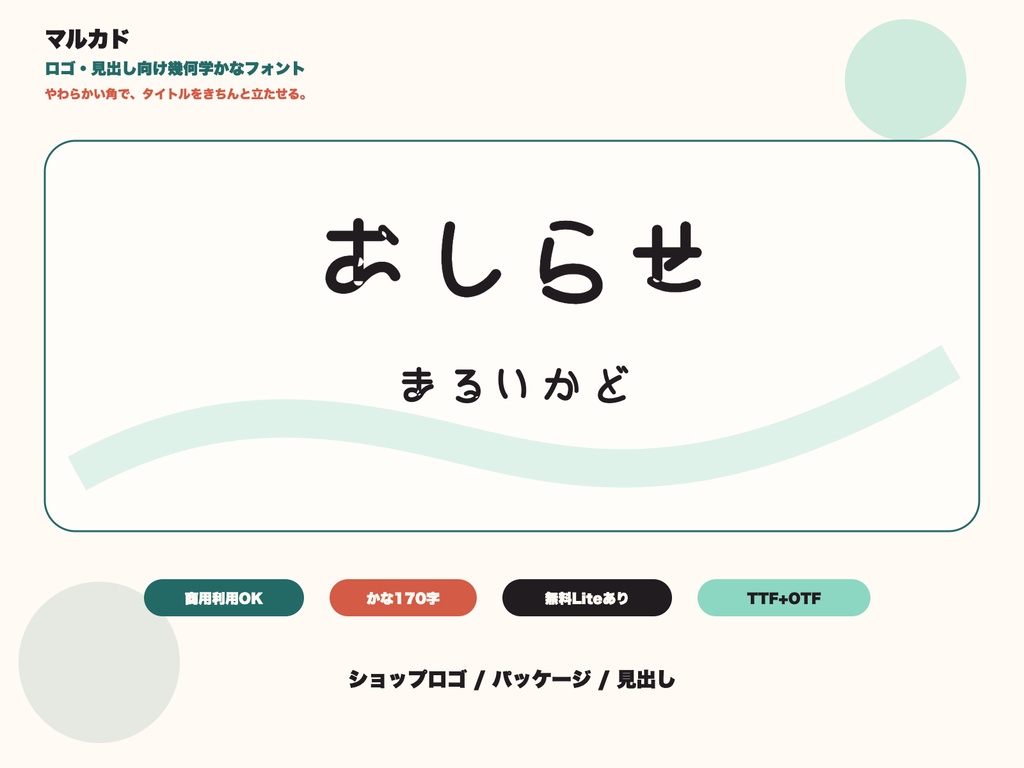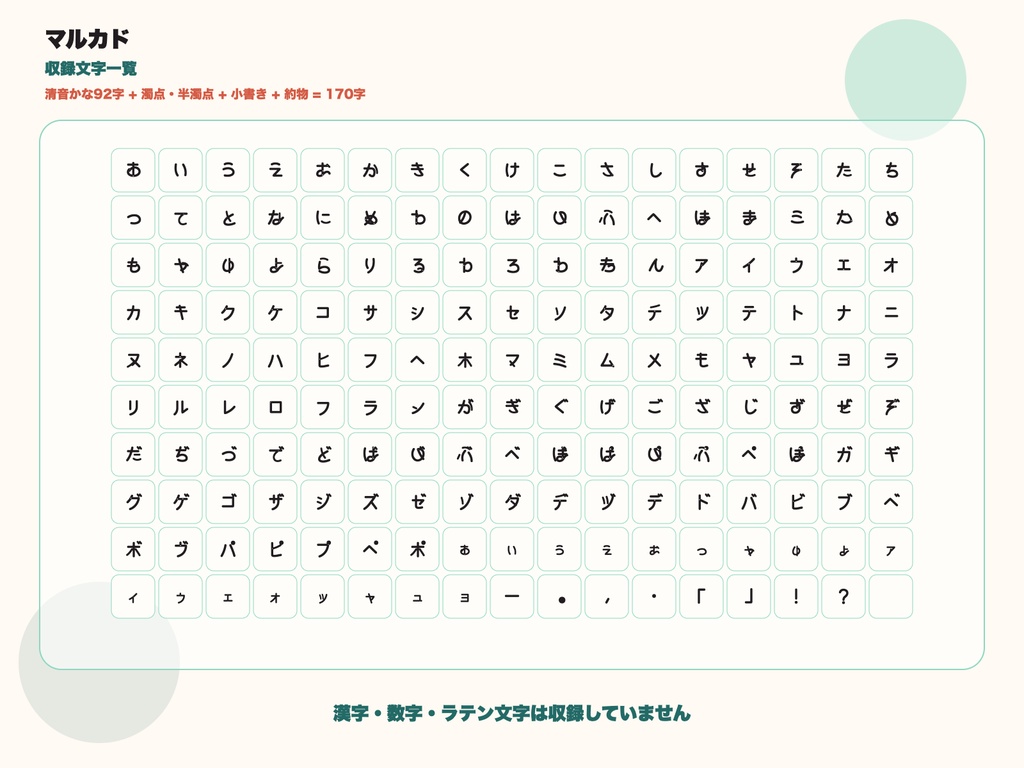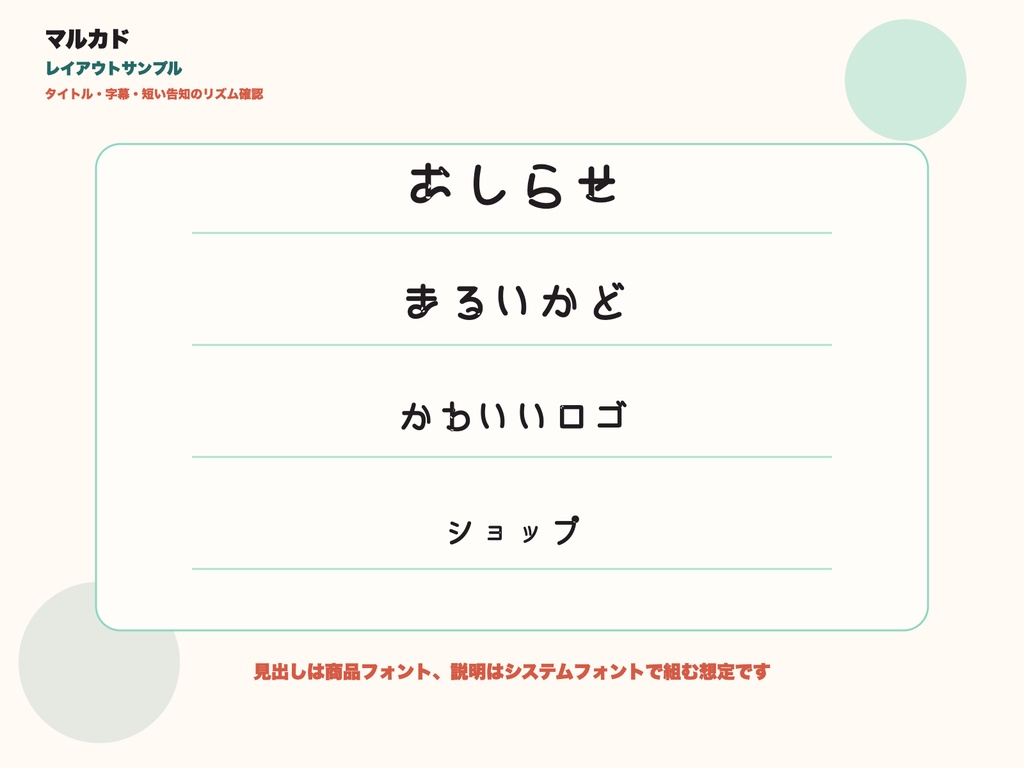
マルカド|ロゴ・見出し向け幾何学かなフォント
やわらかい角で、タイトルをきちんと立たせる。 丸みのある角と、まっすぐな姿勢。「かわいい」だけで終わらせない、ロゴ・見出しのための幾何学かなフォントです。ショップのロゴ、サムネイル、商品ラベル——短い言葉をきちんと主役にしたい場面に。角のニュアンスがそろっているので、小さく置いても、大きく組んでも、画面がだらしなくなりません。 【想定用途】ショップロゴ/配信サムネイル/商品ラベル/イベント見出し ✅ かな170字(ひらがな・カタカナ・記号)/OTF+TTF 同梱 ✅ 商用利用可(クレジット表記不要) ⚠️ フォントデータ単体の再配布・再販売は禁止です。拡張用途・埋め込みライセンスのご相談は SHOP メッセージまで。